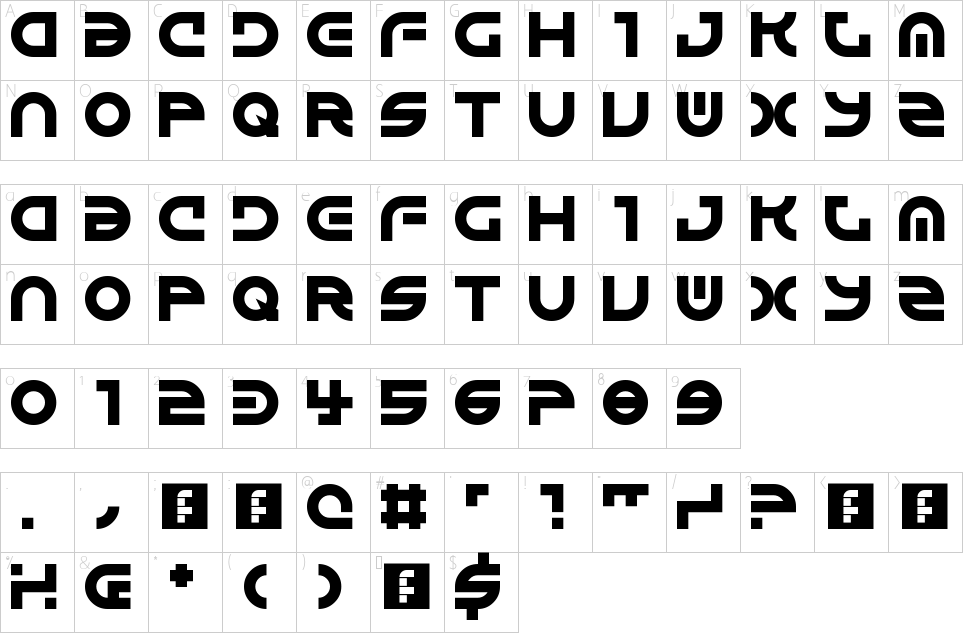
Alienated Font – Fonte Grátis
Alienated Font
Alienated é uma fonte que traz um toque único à sua interface digital, especialmente adaptada para aqueles que procuram algo mais do que o básico em fontes gratuitas. Desenvolvida por Chequered Ink, Alienated oferece uma experiência visual única e desafiadora. Seja você um designer web atento ao detalhe, um desenvolvedor de aplicativos ou simplesmente alguém que busca personalizar o visual de seus projetos, Alienated pode ser o elemento especial que complementa seu estilo. Com um download total de 15.068, é evidente que esta font tem ganho notável de aceitação entre os usuários que valorizam tanto a funcionalidade quanto a originalidade. Numa categoria de fontes gratuitas, Alienated não se limita a ser apenas uma opção de backup, é uma escolha que valoriza a sua criatividade e personalização.